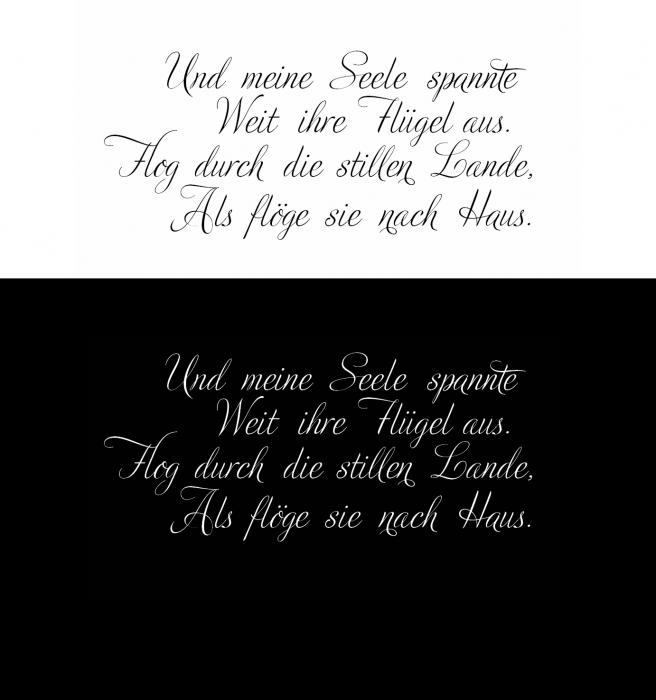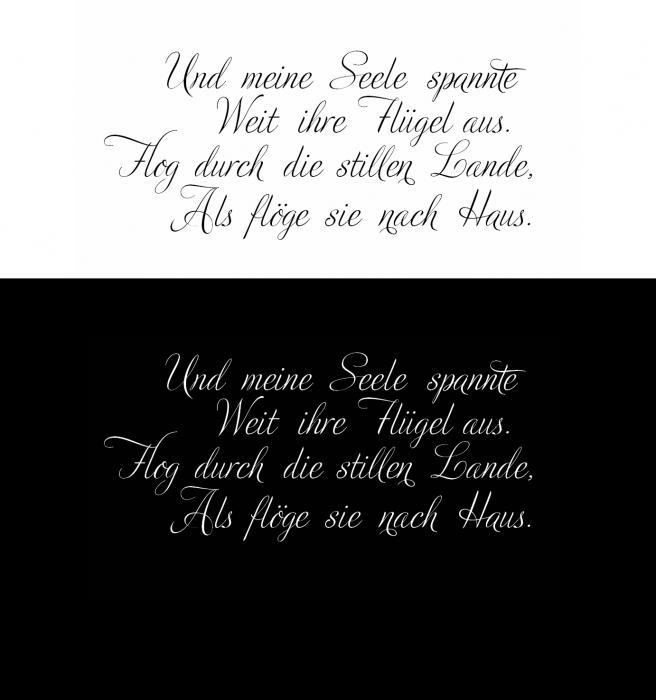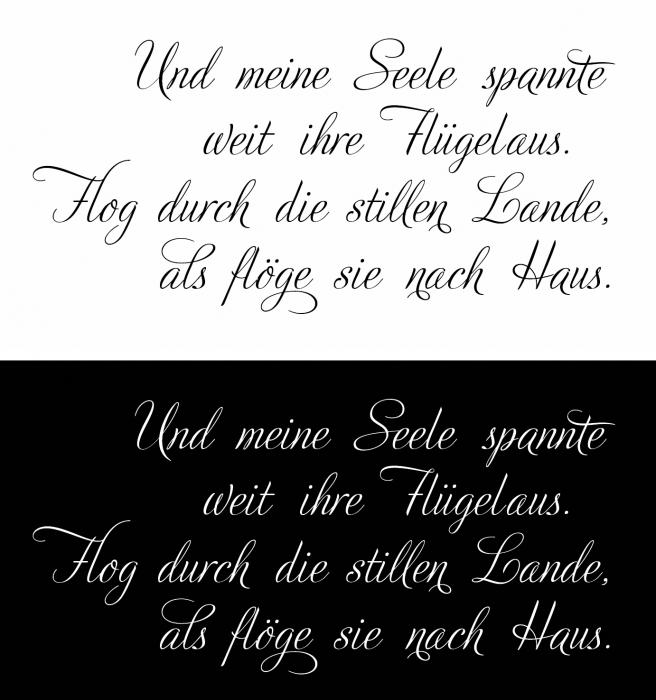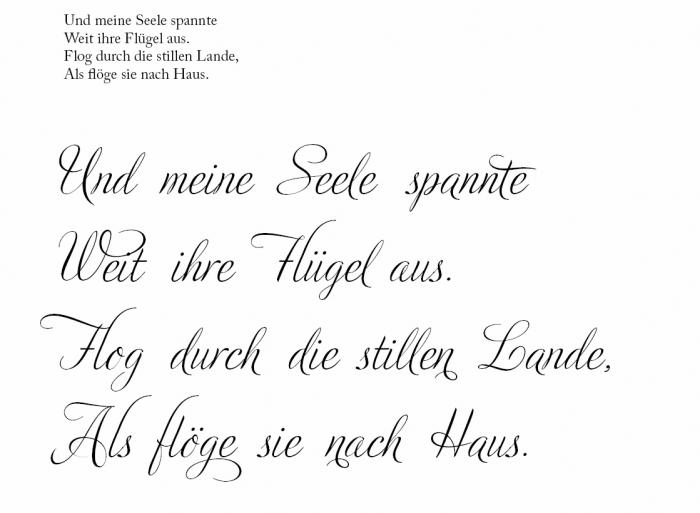
Spationieren von Adios Script Pro
Hallo zusammen, Studium is schon wieder ne weile her und ich hab kein Gefühl mehr dafür, wie ich die Adios Script Pro spationieren soll. Eher eng beieinander, so dass sich die Buchstabenenden (fast) berühren oder eher eine großzügige Spationierung (InDesign 60).
Was ist für eine solche Schrift angemessen. Das ganze soll für ein Tattoo verwendet werden!
Nachdem die Buchstaben anschließen, würde ich nicht von Hand nachjustieren. Zeig einfach mal Beispiele …
Bei einer verbundenen Schrift würde ich nicht nachjustieren, da die Abstände ja schon optimal eingestellt sein sollten. Einzig die Schwünge etc. sollte man hier und da evtl. individualisieren. Da die Schrift aber einige Alternativzeichen hat, kann man sich wohl auch damit schon ein vernünftiges Ergebnis zusammenstellen.
Ich würde es gerade als Tattoo nicht rein linksbündig setzen, sondern auf beiden Seiten flatternd, so dass ein harmonisches Ganzes entsteht.
Mit der Spationierung würde ich wie gesagt gar nichts machen, da scheint mir jetzt manches zu eng.  Aber ich würde die ein oder ander Stelle noch händisch ausarbeiten. Z. B. die unschöne Verbindung von W-Schnörkel und i-Punkt. Wenn du die Zeilen untereinander verteilt hast würde ich noch gucken ob und wie man die Oberlängen noch variieren kann und vielleicht auch bis in die nächste Zeile ziehst, z. B. in die Lücke die das F reißt. Gerade in der dritten Zeilen sind sechs sehr ähnliche Schleifen und drei davon sind wirklich exakt gleich, da würde ich mehr Spiel reinbringen.
Gibt es in der Schrift kein kleines Anfangs-s? Das sieht so ja auch eigenartig aus, würde ich vielleicht eins erfinden wollen, wenn’s das nicht gibt.
Positiv: Die beiden verschiedenen F-Formen und die beiden g sind doch schon mal ganz gut angelegt.
Da ich einen zunehmenden Anteil meiner Arbeitszeit damit verbringe, Todesanzeigen zu setzen, ist der Text für mich ziemlich einseitig besetzt. Wenn der mir als Tätowierung begegnete, würde ich denken, daß da jemand seinen Körper schon mal vorab als Grabstein inszenieren will. Aber vielleicht tue ich Rilke damit auch unrecht.
Ich würde auch den Zeilenabstand wesentlich geringer machen, damit alles etwas komprimierter wirkt. So wie hier:
soll "Weit" und "Flog" "Als" tatsächlich groß geschrieben werden?
Dass der Versanfang groß geschrieben wird, ist eigentlich normal und würde ich auch so lassen.
Es ist eher Eichendorff, ist ja von Schumann so toll vertont worden.
Hallo an alle, speziell an Schnitzel, da er mir ja doch einiges weitergeholfen hat. Ich habe nun noch einmal daran gearbeitet. Ich habe die zweite und vierte Zeile mal klein geschrieben. Eigentlich aus ganz pragmatischen Gründen:
1. Weniger Kringel
2. Weniger Stellen an denen sich Schwünge/Kringel aus unterschiedlichen Zeilen berühren können. Weil die Haut zieht sich ja vielleicht später zusammen, daher ist luftig vielleicht besser. Wenn das aus Sicht der Germanisten aber ein "nogo" ist, werde ich das wieder ändern. Meine Schwester is Germanistin, also mal abwarten. Ich bin immer noch nicht zufrieden mit dem Resultat.
ein blick in mir verfügbare gedichtanthologien (auch online und auch älteren datums) zeigt, dass die anfangsbuchstaben der verse immer groß geschrieben werden, also:
Und meine Seele spannte
Weit ihre Flügel aus,
Flog durch die stillen Lande,
Als flöge sie nach Haus.
Weil die Haut zieht sich ja vielleicht später zusammen, daher ist luftig vielleicht besser
Irgendwann ganz viel später dehnt sie sich dann aber auch wieder ;-) …
„spannte“ hat noch das falsche s am Wortanfang würde ich sagen oder es muss eine bessere Verbindung der Buchstaben geschaffen werden und zwischen „Flügel“ und „aus“ braucht es in meinen Augen noch mehr Platz sonst verschmelzen die Worte (besonders auf beweglicher Haut und Tätowierern mit nicht ganz ruhiger Hand). Auch insgesamt würde ich nochmal einen Blick auf die Buchstabenverbindungen werfen und ggf. von Hand anpassen, besonders p-a in „spannte“, o-g in „Flog“, f-l-ö in „flöge“ und H-a in „Haus“.
Ich sprach nicht von Bleisatz, ich arbeite auch digital, oft auch mit Schreibschriften und der Mühsal, ihr mit Alternativen den Anschein von Handschrift zu geben und ihr die Monotonie auszutreiben. In einzelnen Wörtern ist das durchaus gut machbar, aber in Text?
Wer ist »man«? Vielleicht ist es mutig, aber ich glaube, daß nicht nur ich an jedem vierzeiligen Text sehr schnell sehe, ob er geschrieben oder gesetzt ist. Der Satz ist immer die billigere Variante, und selbst wenn es nur wenige sehen: der Tätowierte weiß es.